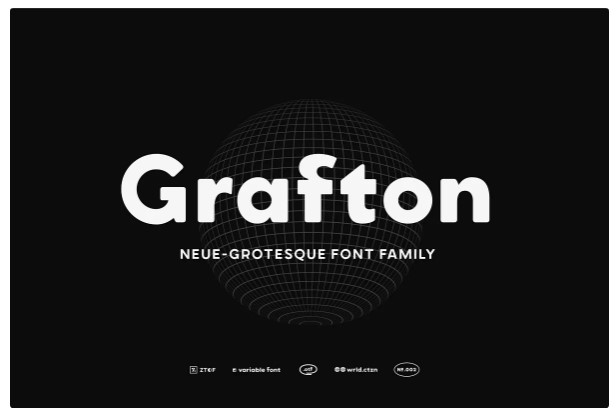
ZT Grafton - это неогротескный шрифт, основанный на геометрических формах с современными, дружественными и сильными эмоциями.
Он был создан с нуля, чтобы быть спокойным, гладким и чистым, а тонкое гуманистическое влияние добавляет теплоты этому шрифту.
Он доступен в восьми вариантах веса и поддерживает 100+ языков на основе латиницы.